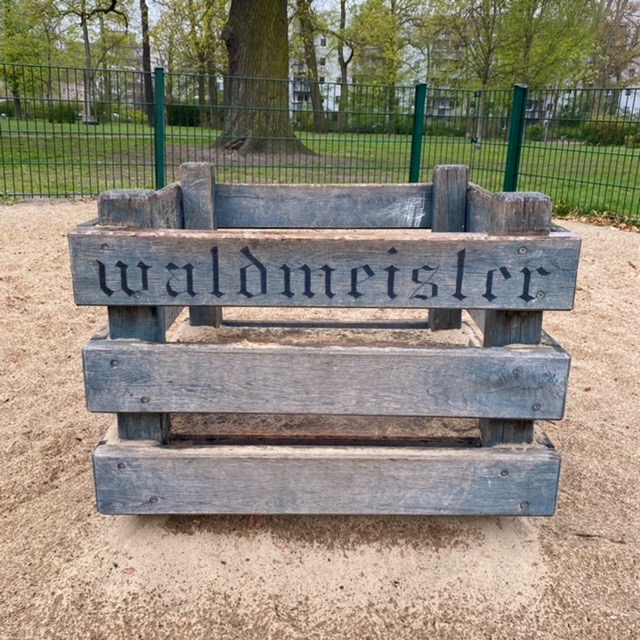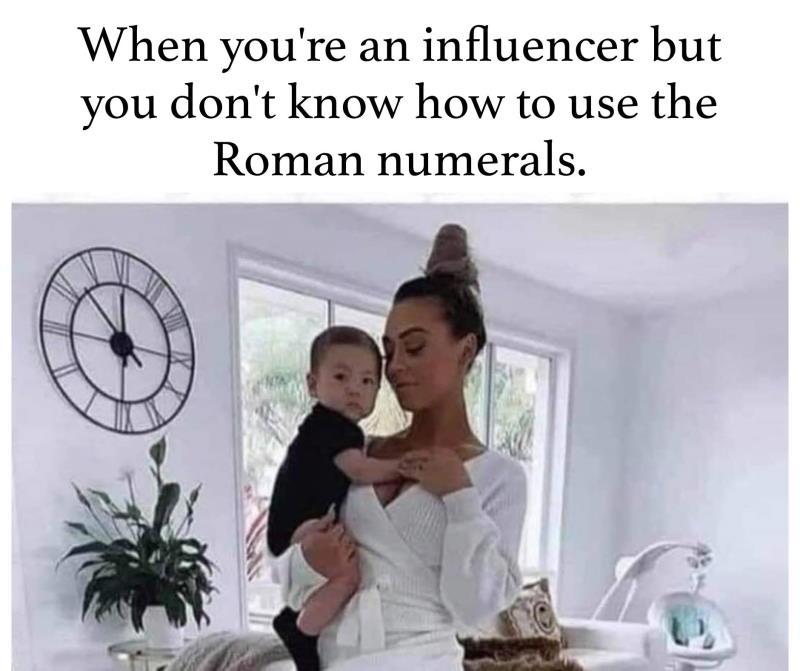
Ein paar spezielle Fonts fürs Coding in Aktion: https://coding-fonts.css-tricks.com/
Mir gefallen in dieser Liste die "Gintronic" und die "Mona Lisa" sehr gut ... gerade das "r" der Gintronic, finde ich, ist sehr schön im Vergleich zu einigen anderen Schriften der Liste. Die Comic Neue ist natürlich auch lustig 😉
Spielplatztypografie ... :shock:
:.Spielplatz..  Eine, wie ich finde gute Idee, die Kleinen zunächst mal neugierig zumachen auf   "die andere Schrift".  Vielleicht findet sich der Eine oder Andere, der sie auch lernen  will. Wäre  m.E. zu begrüßen.
Unterſchied
Ralf hatte zum Gebrauch des langen s im heutigen Fraktursatz vor einiger Zeit sehr schlüssige Überlegungen gepostet. Leider finde ich die Passage nicht mehr.
Wenn's jemand das dann lernen will, wird hoffentlich auch der kleine Unterſchied gelernt ...🙄
Muß ja nicht bei Jedem  so laufen wie bei mir:  Weil mir die Schrift befremdlich vorkam, und ich mich schwer damit tat, sie  zu lernen, bekam ich von
einem  Freund der Familie, einem  Studienrat zur Konfirmation  Gustav Frenssen's " Jörn Uhl " geschenkt. In Fraktur gesetzt. Das hat geholfen.
Im Kunstunterricht kamen  dann noch etliche andere Varianten dazu. die ich alle schätzen und lieben gelernt habe. Für mich stellten sie  ein unver-
zichtbares Kulturgut dar, wie auch die Kurrent.
Aktion ›Reclaim Blackletter‹!
Scrap Metal ... :huhu:
Kann man das Schreiben datieren?
Leider nein. Ich tippe auf 1950er Jahre aber es könnte auch aus den 1930ern sein …
Leider nein. Ich tippe auf 1950er Jahre aber es könnte auch aus den 1930ern sein
Die Wiederverwertung abgenutzten Typenmaterials wird wohl so alt wie die Druckkunst sein, wurde auch von den Gießereien aktiv beworben (s. u.), denn man wollte ja immer neue Schriften verkaufen. Ich kann mir da gut einen schwäbischen Drucker vorstellen, der mit einem hartnäckig-behäblichen "des duad's nô"  seinen Gießereivertreter auf die Palme bringt.
conterclockwise
:-?Die hängt doch nur Kopf, ist vielleicht eine australische Ausführung.
Die hängt doch nur Kopf
Ist vielleicht 'ne Yoga-Influencerin, 24/7 Kopfstand …